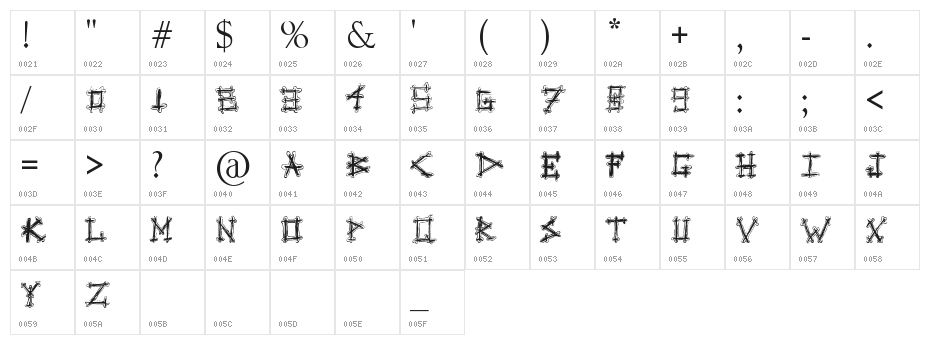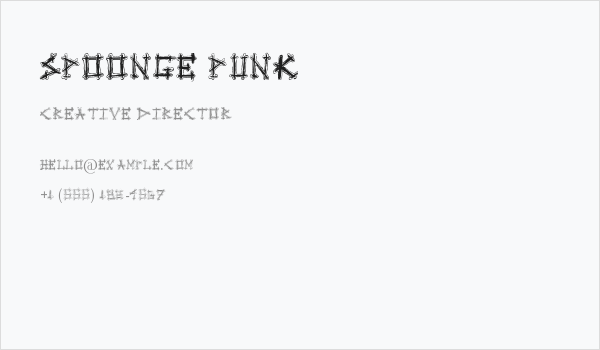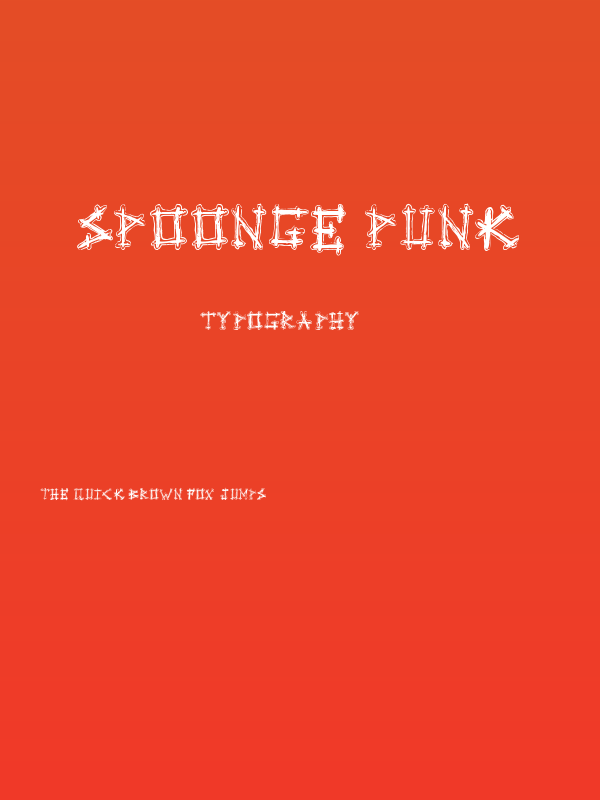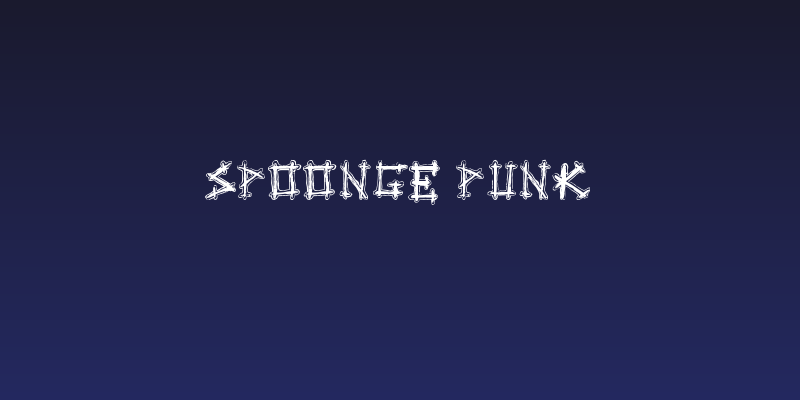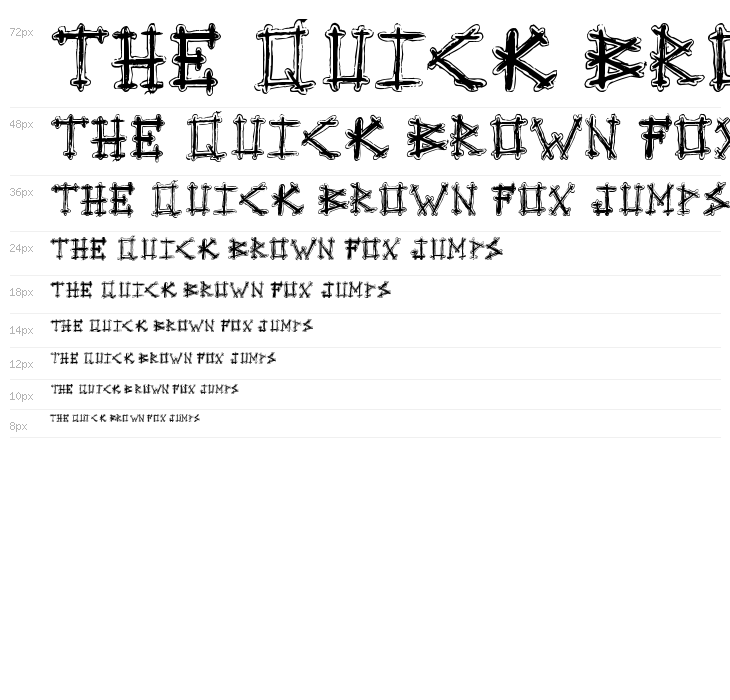
Spoonge Punk Font
SPOONGE-PUNK MAIUSCOLE
SPOONGE-PUNK MINUSCOLO
SPOONGE-PUNK ALTRI CARATTERI
| Nome | Spoonge Punk |
| Stile generale | Punk, Edgy, Rebellious |
| Progetti proposti | Ideal for music album covers, event posters, streetwear branding, and edgy graphic designs. |